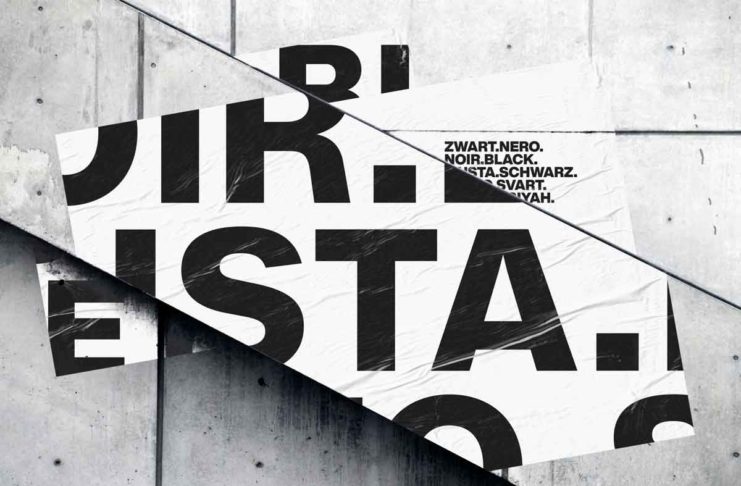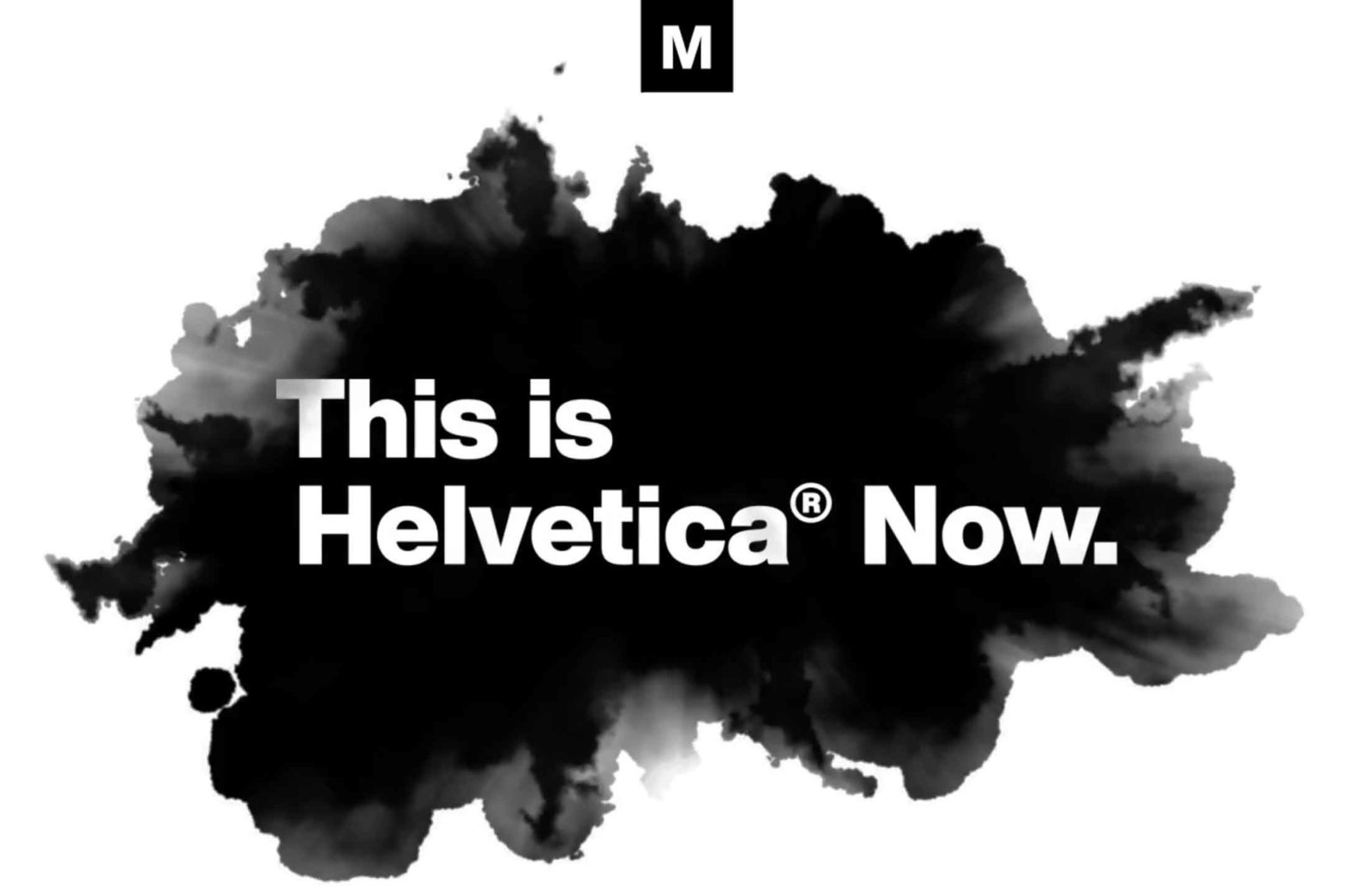
Helvetica Now, il font più famoso di sempre si rinnova dopo 35 anni
Helvetica Now è la versione moderna e rivista del font più famoso e diffuso di sempre: non a caso era integrato di serie con il primo rivoluzionario Macintosh del 1984.
Il nuovo font Helvetica Now arriva da Monotype, azienda nota in ambito tipografico per la creazione di caratteri di stampa: ricordiamo che l’originale e famosissimo Helvetica è un carattere tipografico creato nel 1957 da un’idea di Eduard Hoffmann, direttore della fonderia Haas di Münchenstein in Svizzera, disegnato da Max Miedinger.
Helvetica​​ Now è una famiglia di font che Monotype dice di avere riprogettato “rispettosamente e con molta attenzione” per l’era moderna. Si tratta di 48 font con tre dimensioni ottiche (asse che permette di usare un carattere garantendo leggibilità ottimale a una determinata dimensione, con disegni che tengono conto dell’occupazione specifica di dimensione e spazi occupati).
È la prima volta in 35 anni che il font Helvetica viene ridisegnato e, secondo i nuovi progettisti, il design è ancora più ricercato ed elegante di prima.
Helvetica​​ Now, la versione moderna e rivista del font Helvetica
Helvetica è uno dei font più famosi di sempre. È un san-serif (senza grazie) molto lineare. La sua semplicità e chiarezza lo rendono utile in vari frangenti ed è usatissimo: in poster, pubblicità, marchi aziendali, nel signage per i sistemi di trasporto, nelle stampe d’arte e in moltissimi alri campi della comunicazione.
Dal 1989 il font Helvetica è – tra le altre cose –  il carattere tipografico ufficiale per l’intera segnaletica della città di New York, dalla metropolitana ai treni, dai cartelli stradali alle mappe della città. Su Mac è incluso fin dal primo modello del 1984 come carattere di sistema, scelta che contribuì non poco alla sua diffusione.
Come accennato, questo carattere fu ideato dal designer elvetico Max Alfons Miedinger, ma richiesto da un altro svizzero, Eduard Hoffmann, che nel 1957 era a capo della fonderia tipografica Haas, fondata nel 1600 a Basilea. Il nome che venne assegnato inizialmente al font era “Neue Haas Grotesk”, (l’indicazione “Grotesk” fa riferimento una tipologia di caratteri senza grazie); nel 1960 venne rinominato Helvetica, usando l’aggettivo latino di Svizzera.
Il nuovo Helvetica Now offre tre varianti ottiche: Micro, Display e Text. Helvetica Now Micro è indicato come ideale per risolvere problemi di leggibilità anche in documenti con testi di piccole dimensioni (da 4 a 7 punti).
Helvetica Now Micro offre più aperture, forme ampie e una x-height  (letteralmente l’altezza della “x”) superiore, accenti più evidenti, aggiustamenti ottici e varie piccole rifiniture che consentono di migliorare ulteriormente la lettura. In genere la dimensione ottica di un font più piccolo, ad esempio 10 punti, comporta minor contrasto tra linee spesse e sottili, una altezza maggiore e una spaziatura maggiore rispetto ai font progettati per una dimensione ottica di 72 punti.
Helvetica Now Display offre “peso” (riferimento allo spessore di un testo) variabile da “Hairline” ad “Extra Black” con spaziature appropriate indicate dai 14 punti in poi. Usando questa variante non è necessario il trimming (la rimozione di spazi indesiderati) o interventi manuali alla spaziatura e al kerning ottico, il ridimensionamento e riposizionamento di segni di interpunzione in alcuni casi necessario con la vecchia versione.
Helvetica Now Text è indicato come “una bestia da soma”, disponibile con “pesi” che variano da “Thin” a “Black” con curata attenzione alla spaziatura e al kering. A detta di Monotype è piacevole da leggere e integra un’ampia palette di simboli adatti a chi si occupa in modo professionale di design.